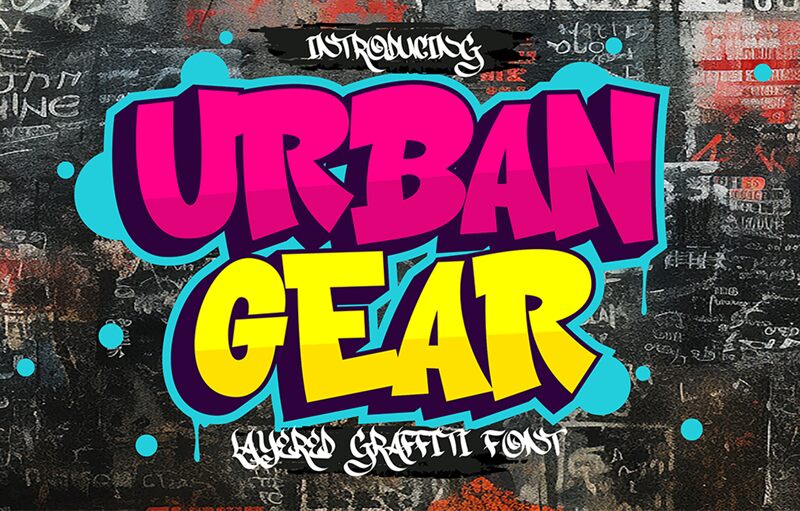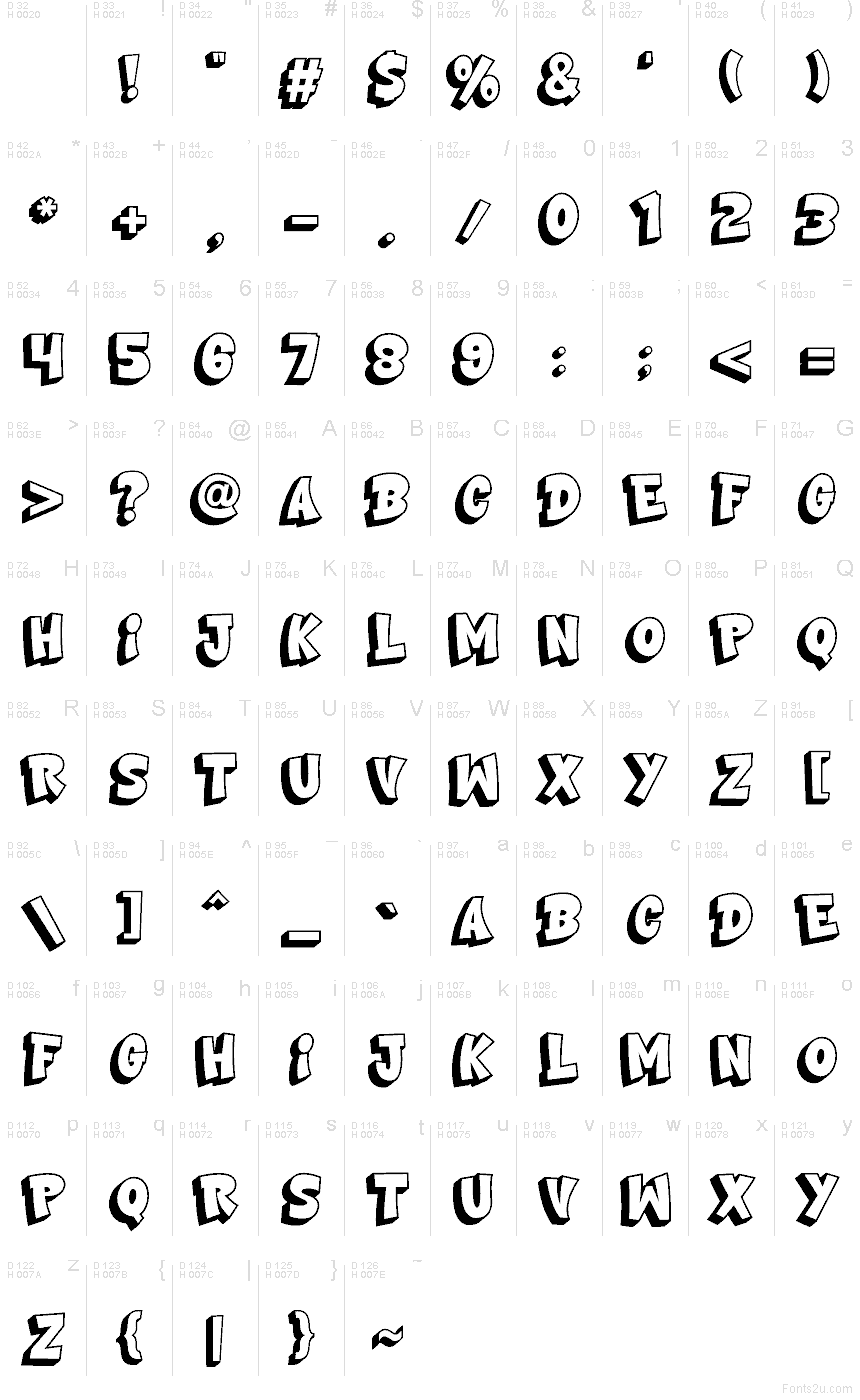
Urban Gear Extrude od Cikareotype Studio je bezplatné komiksové písmo typu display, které definují velké, nakloněné znaky a výrazná černá extruze, díky níž design působí jako plakátová grafika. Nepravidelné úhly a silueta připomínající výstřižek dodávají písmu náboj ručně kreslených pouličních nápisů namísto uhlazeného a sterilního 3D vzhledu.
Tento grafický akcent se skvěle hodí na herní miniatury, záhlaví pro YouTube, letáky na akce pro děti, komiksové plakáty nebo obaly snacků a streetwearového oblečení. Nejlépe vynikne v krátkých titulech, kde hloubka a nepravidelný rytmus promění pár slov v nepřehlédnutelný, úderný nadpis.